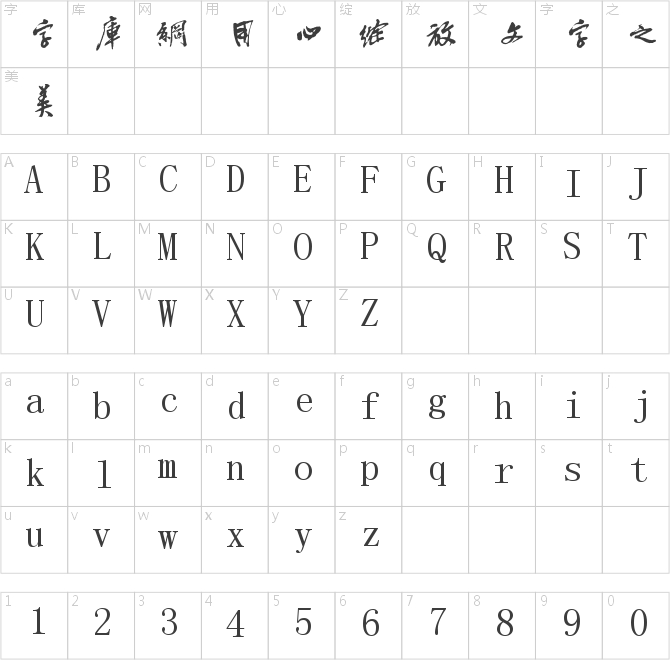
字酷堂苍石行书(个人非商业) 详情页
字体名称: 字酷堂苍石行书
字酷堂苍石行书(个人非商业)
字酷堂苍石行书(个人非商业)介绍
字酷堂苍石行书(个人非商业)字体字库是一款让人赏心悦目、百看不厌的中文字体,适合各类广告和产品包装设计应用,字体大小8.53MB,格式为ttf字体,上传用户是随缘゜,作者/版权方为字酷堂